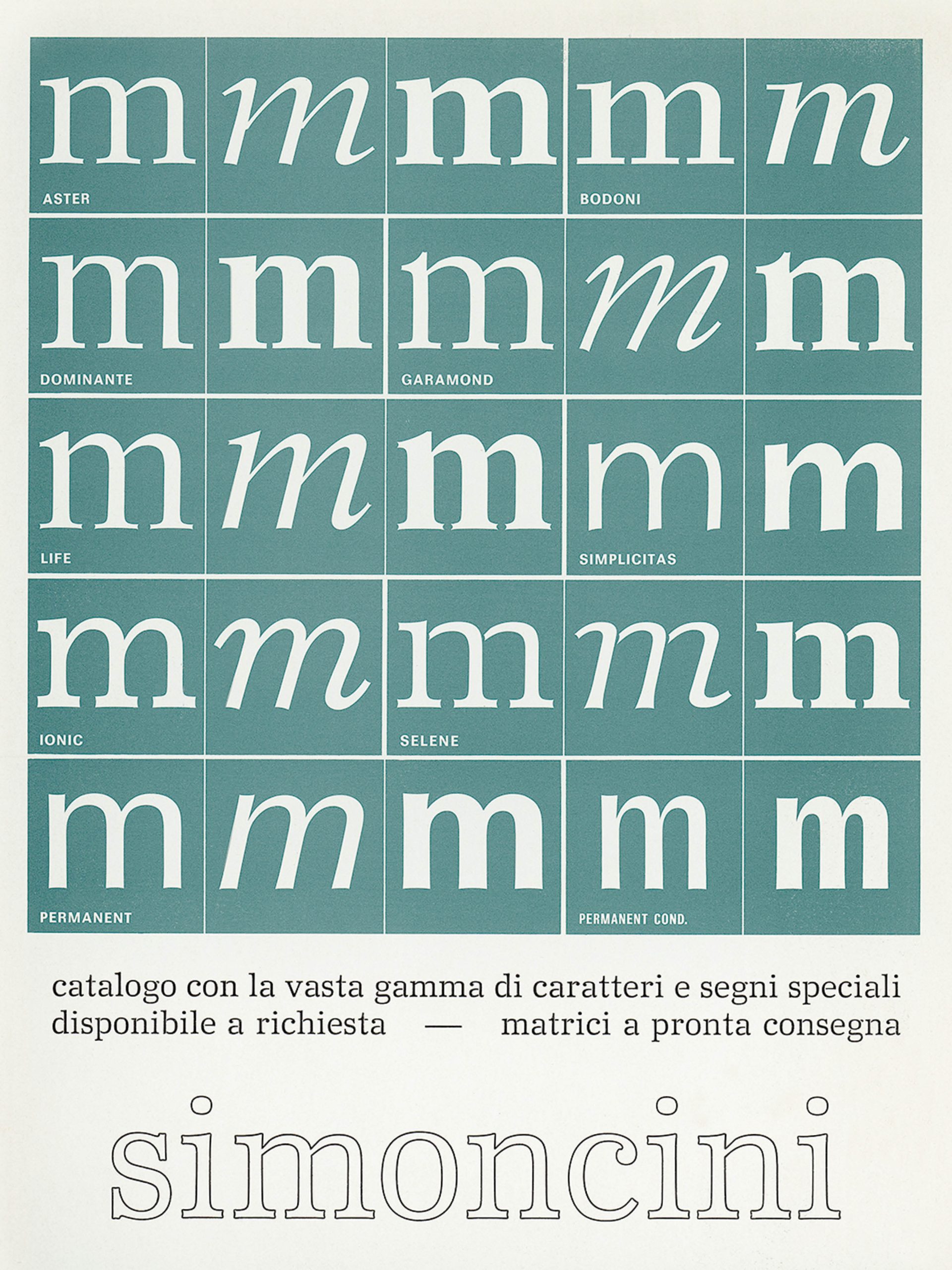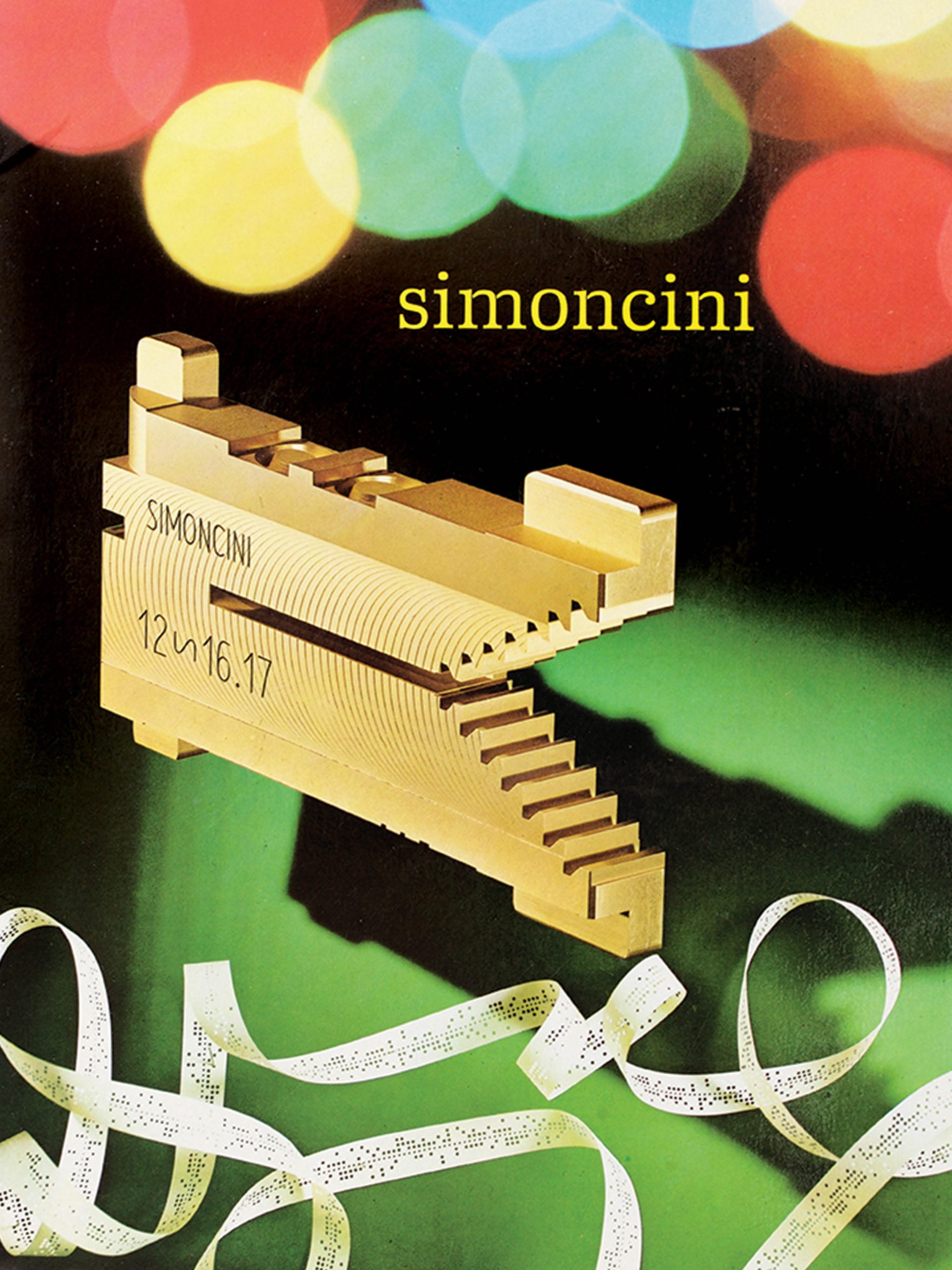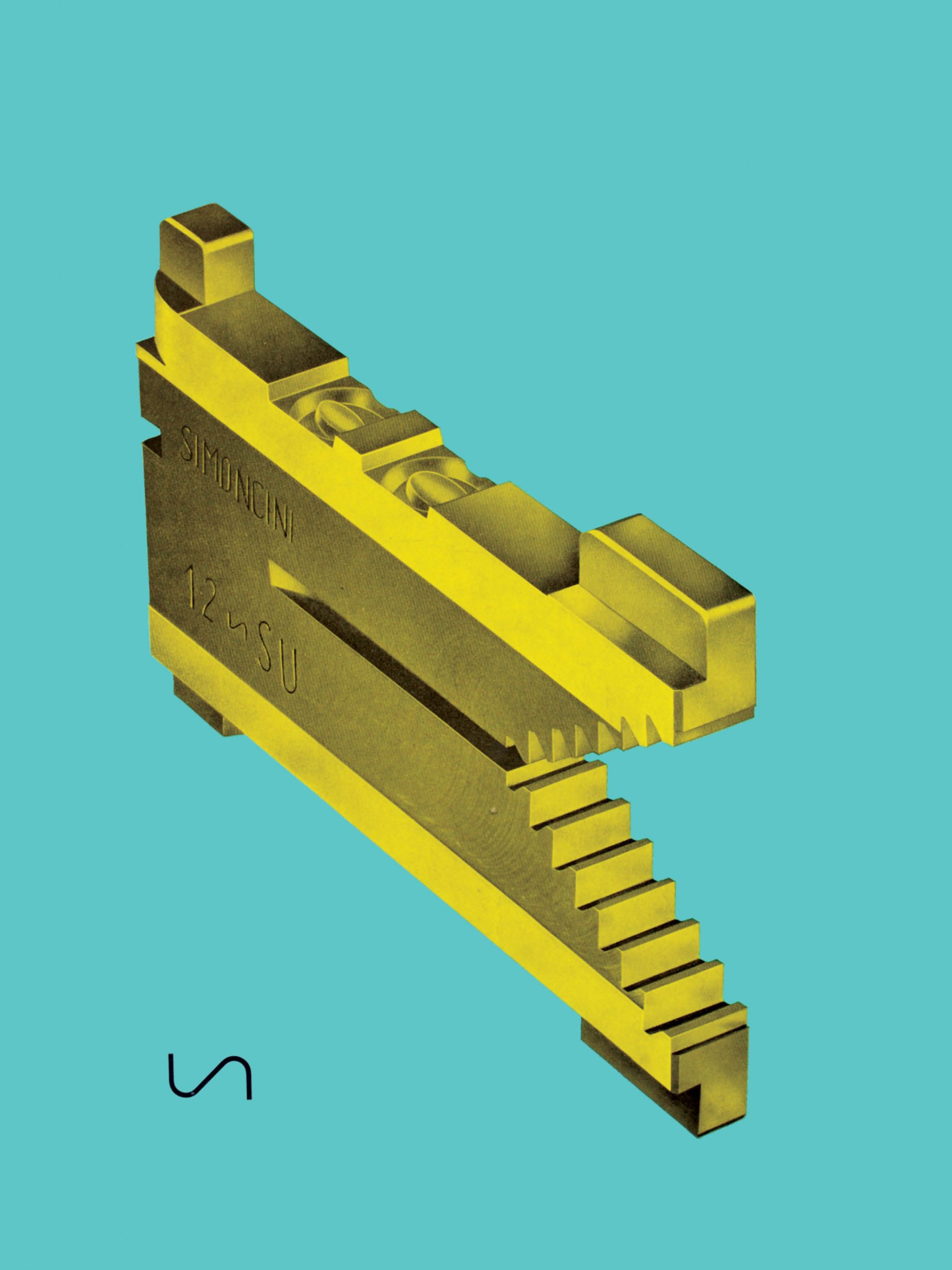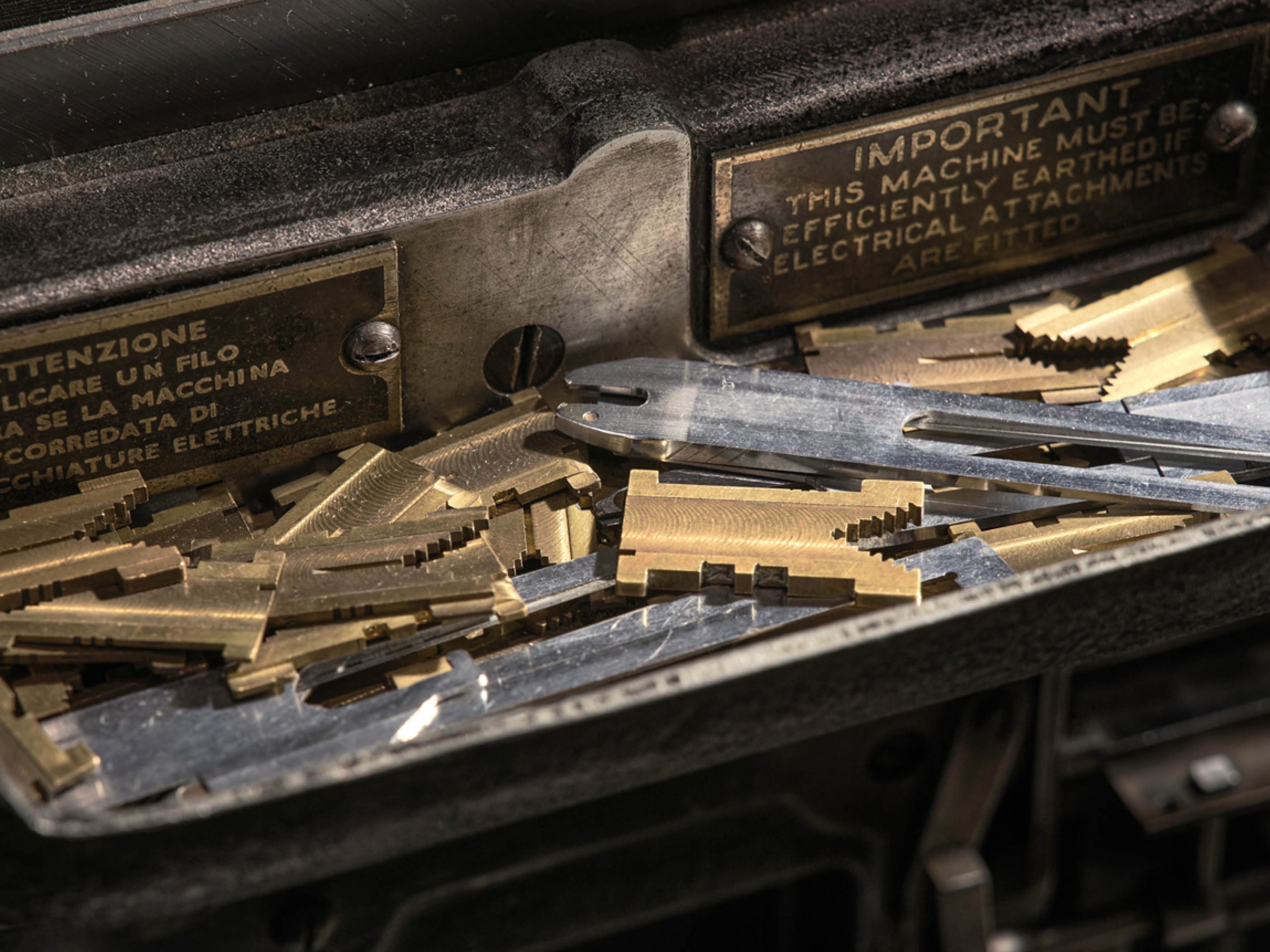
Francesco Simoncini
Data la sua praticità e velocità, la Linotype ebbe un forte successo anche in Italia. Uno dei nomi italiani più importanti legati a questa macchina rivoluzionaria fu sicuramente quello di Francesco Simoncini (1912-1975). Imprenditore bolognese dalle idee innovative e progettista autodidatta di caratteri per la stampa, Simoncini riuscì a trasformare la piccola officina paterna di riparazioni per Linotype in una grande industria internazionale per la progettazione e produzione di caratteri, con una attenzione particolare alla creazione delle matrici. Simoncini si è sempre posto come obiettivi essenziali la chiarezza e la leggibilità: questa attenzione, unita alle capacità imprenditoriali e alla diffusione della tecnologia Linotype, fece sì che a partire dagli anni Cinquanta i suoi caratteri ebbero largo impiego in ogni ambito della stampa in Italia: dal Delia, progettato per gli elenchi telefonici, al Garamond Simoncini, impiegato dalle edizioni Einaudi a partire dal 1960 e divenuto il carattere più emblematico e rappresentativo dell’editoria italiana del dopoguerra, utilizzato anche al giorno d’oggi da alcune tra le principali case editrici.